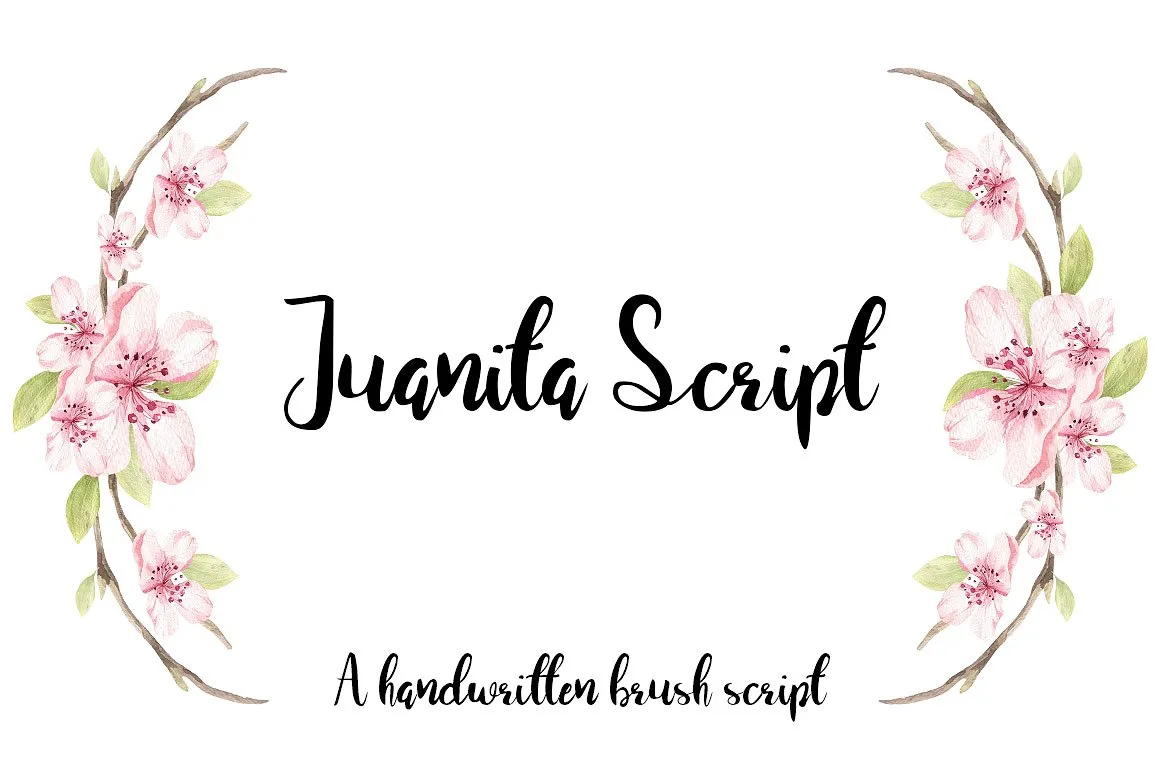
Juanita Script Font – Download Grátis
Introduzimos a Juanita Script Font! Desenvolvida por Webcodesigns, esta é uma fonte Brush que foi feita à mão com pincelado. Com dois estilos, suave e rústico, ela permite ao seu próximo projeto adquirir o encanto característico da escrita manuscrita. Ideal para aqueles desejando dar um toque de criatividade e personalização especial aos seus projetos digitais. Este pincel curioso e irregular é perfeito para criar um aspecto que está em alta neste momento. Seja você um designer ou um criativo, a Juanita Script pode ser o ponto final para tornar seu trabalho único e diferenciado. Descubra como transformar suas ideias digitais em obras de arte à mão!